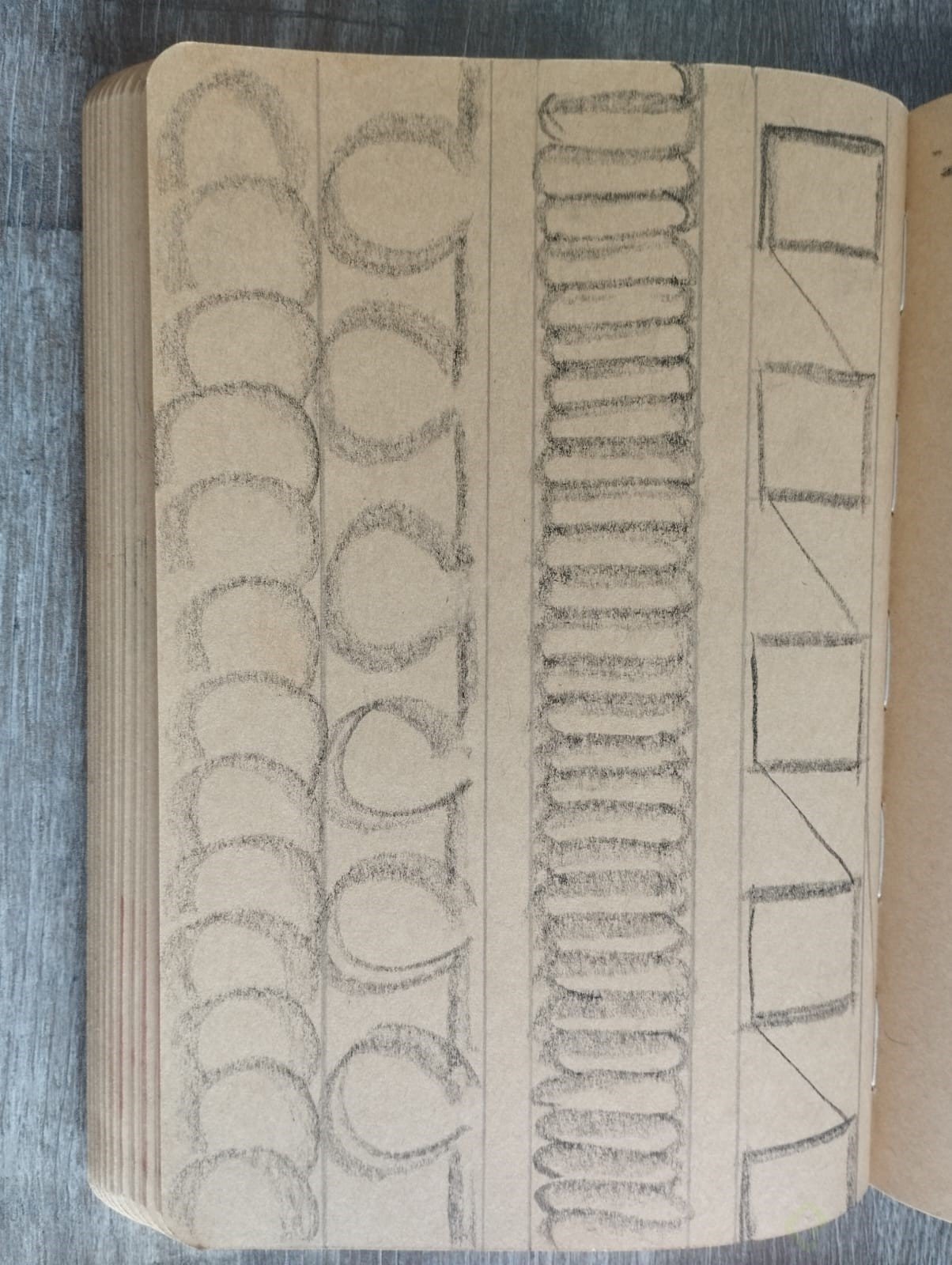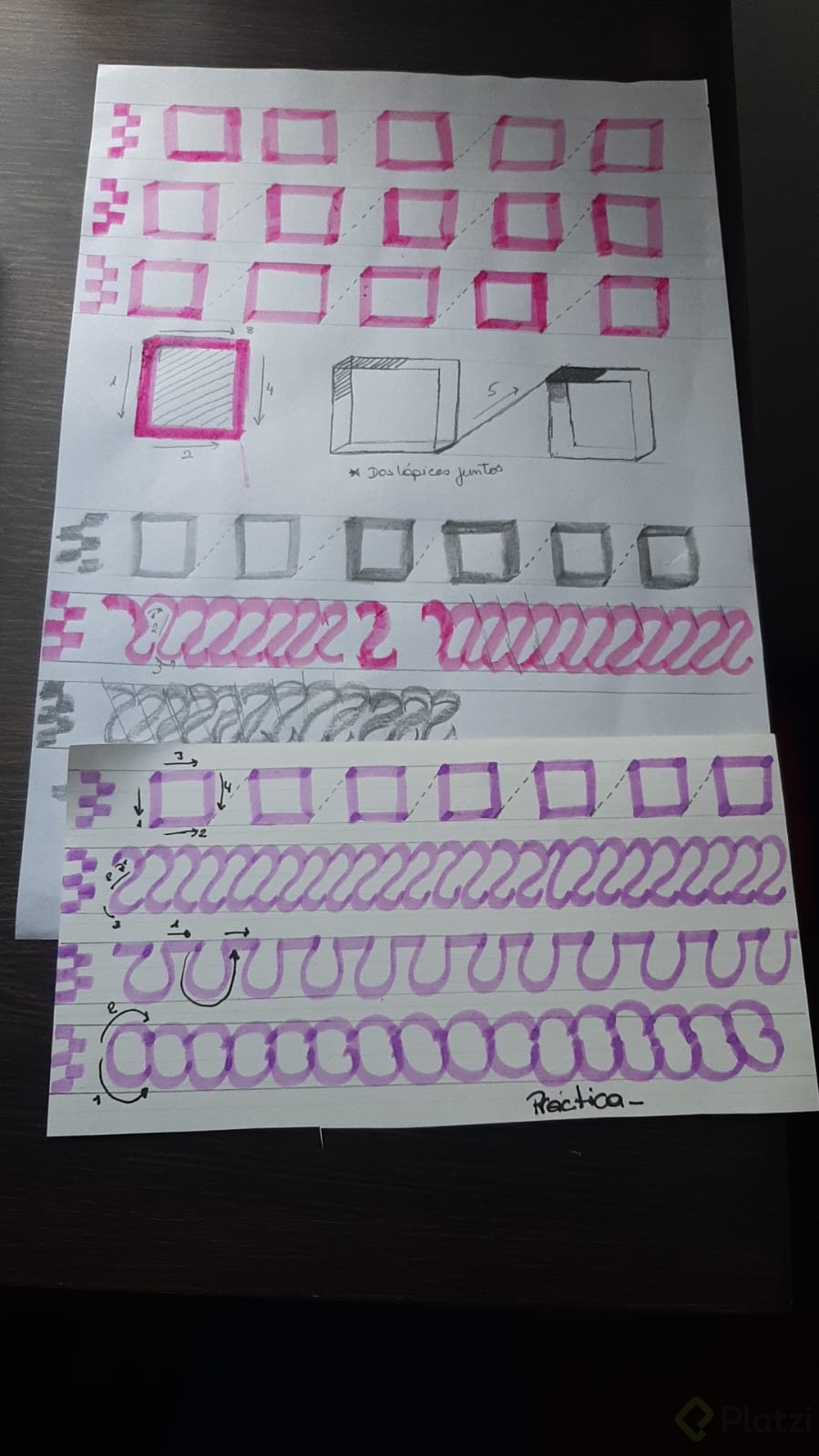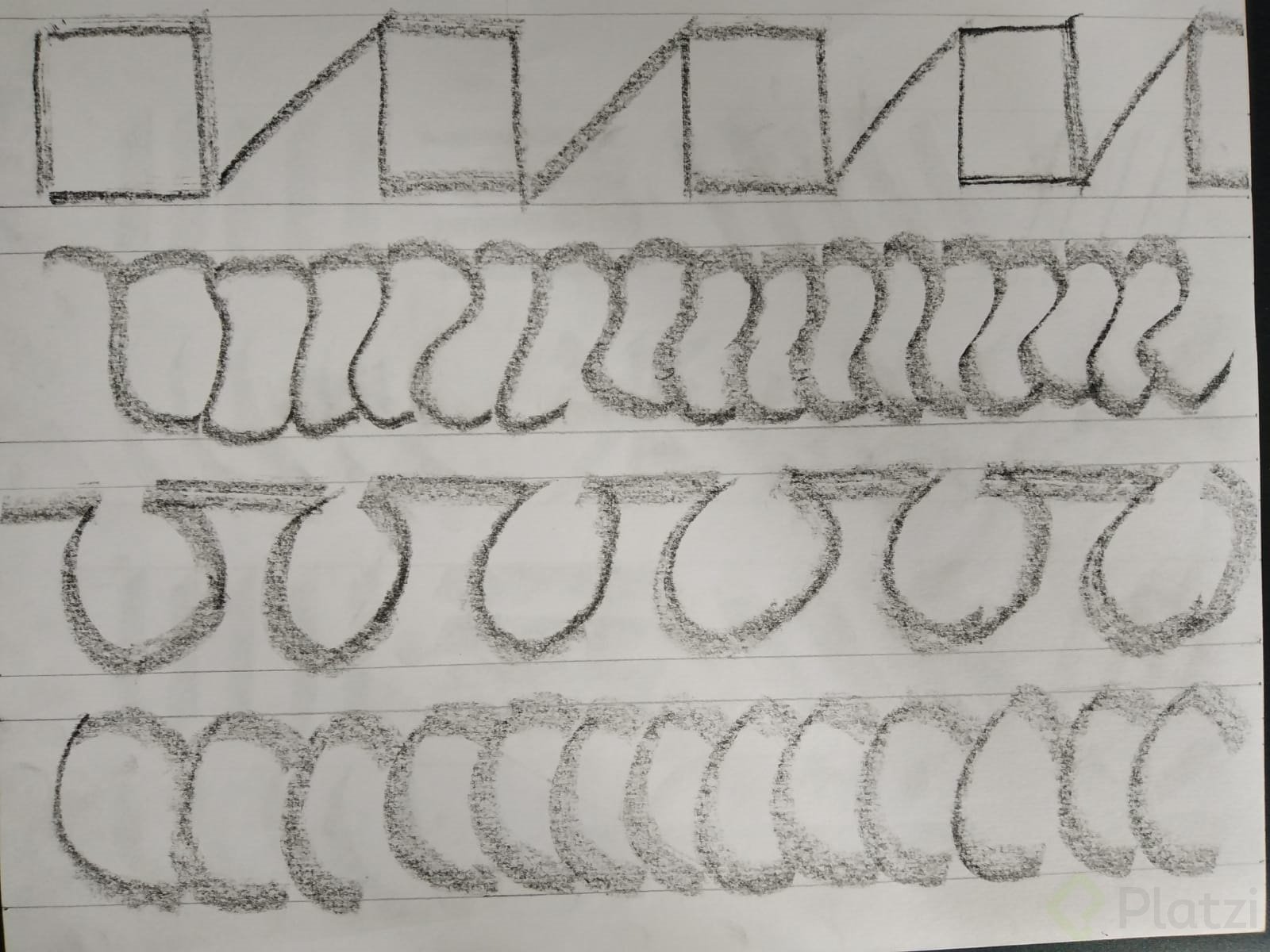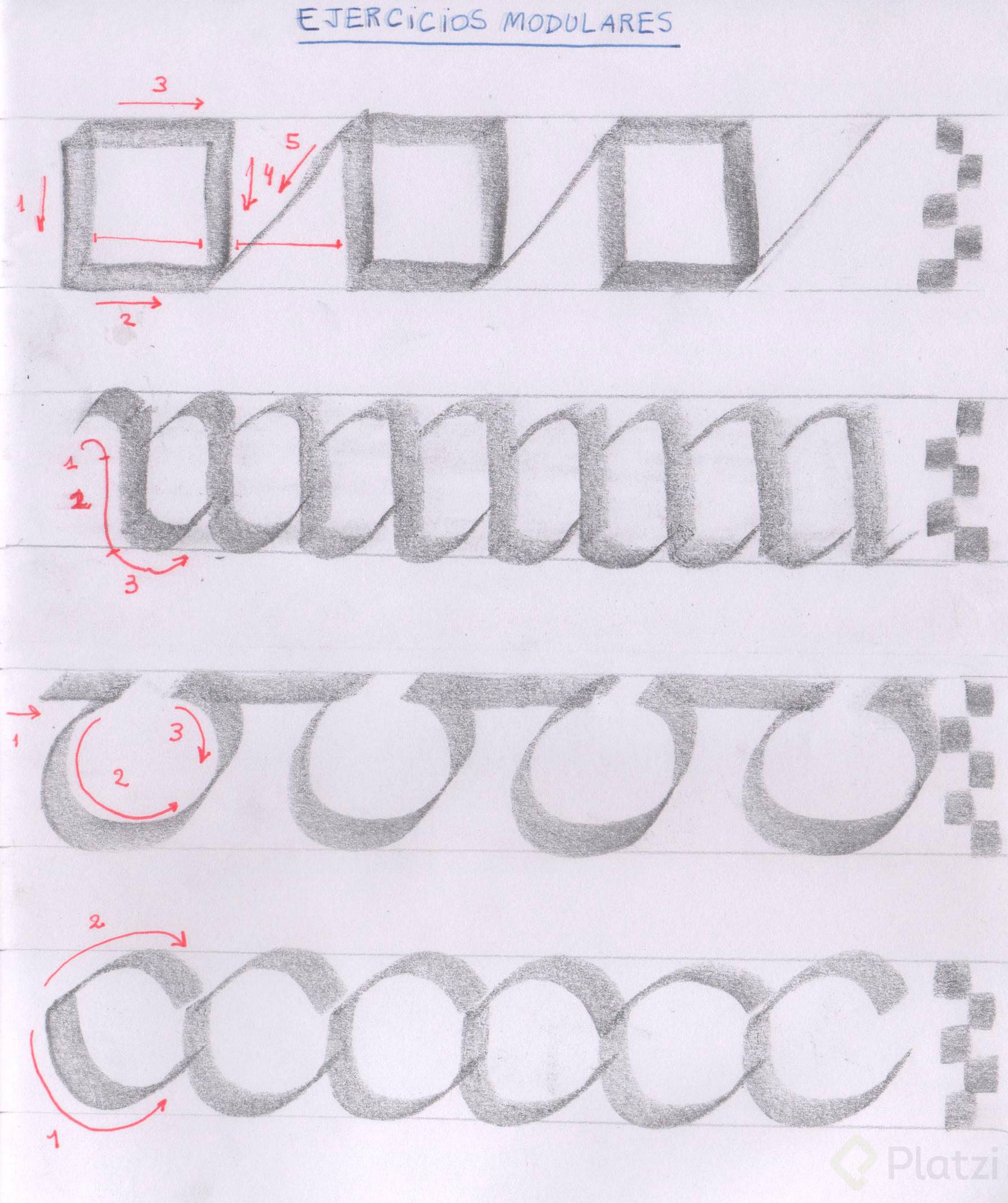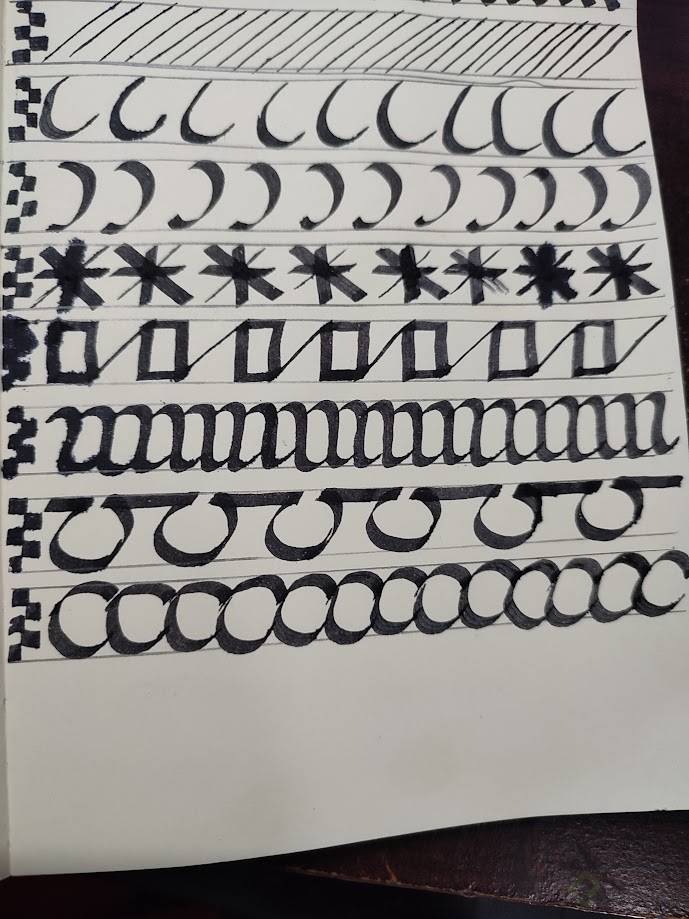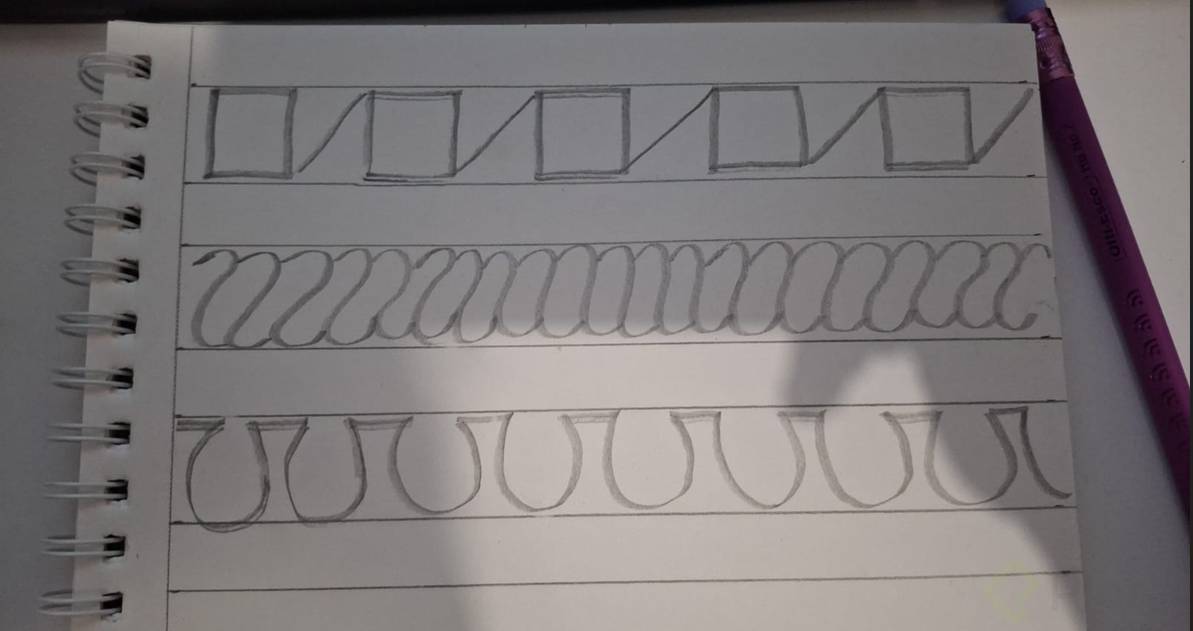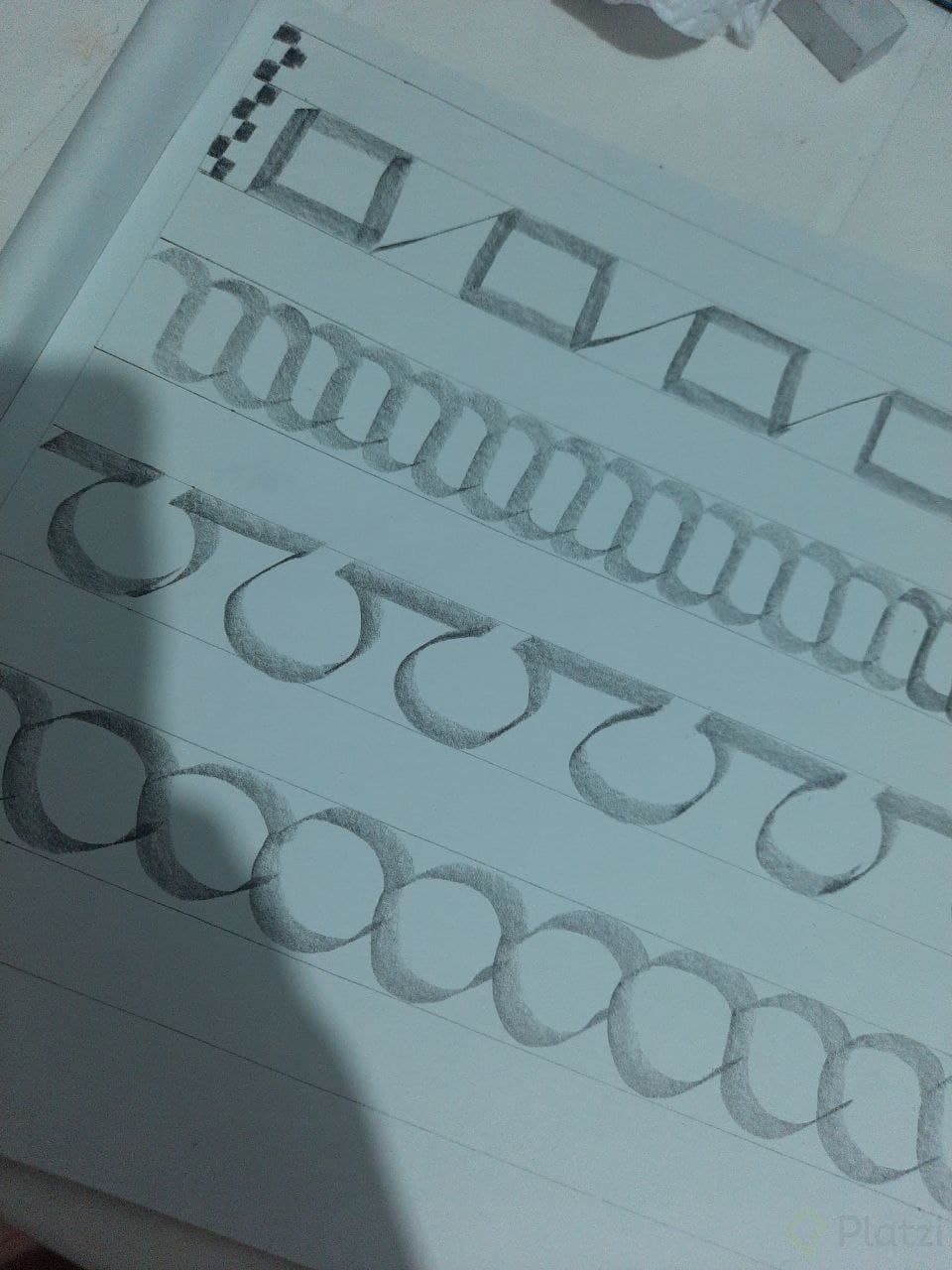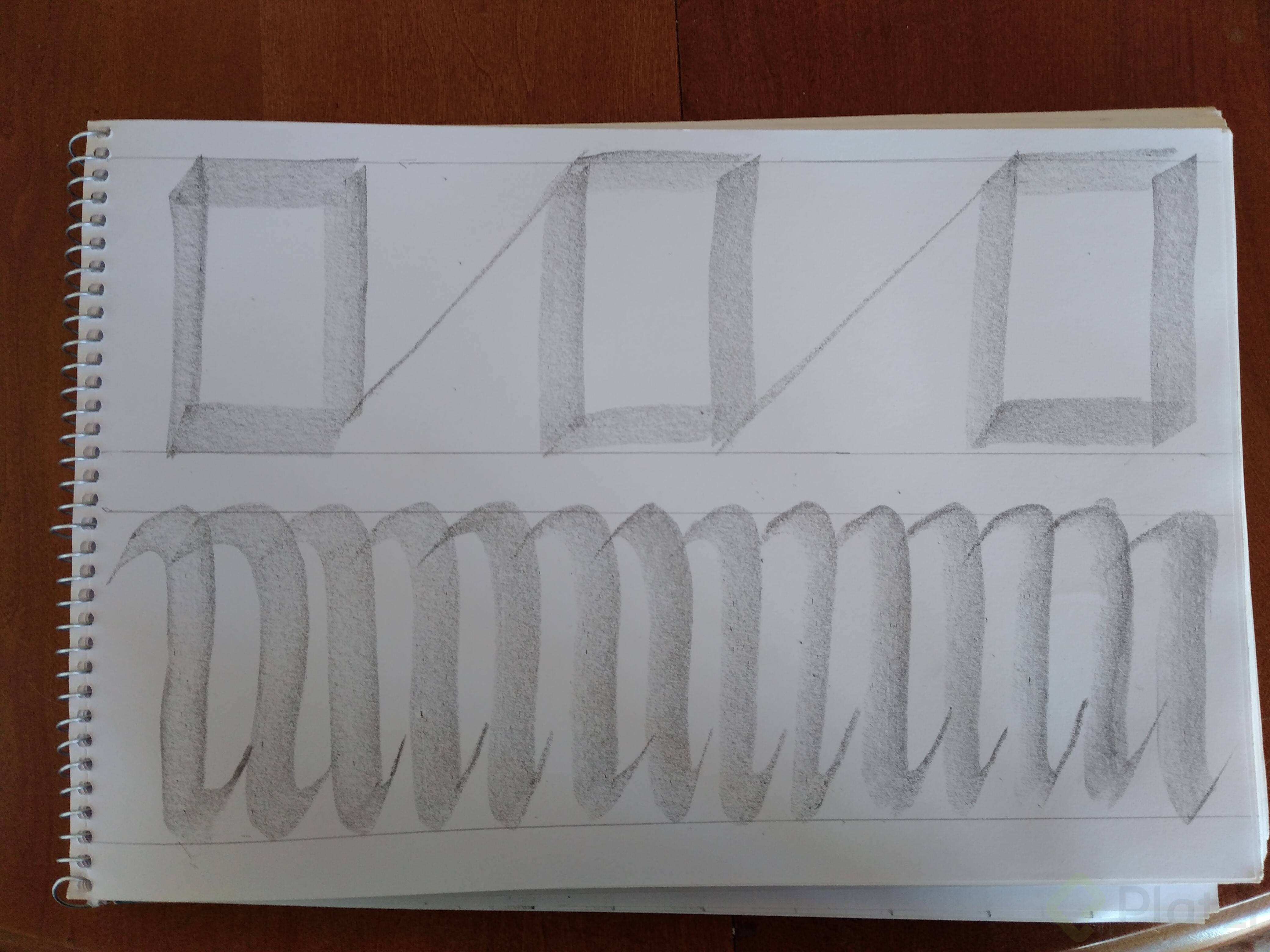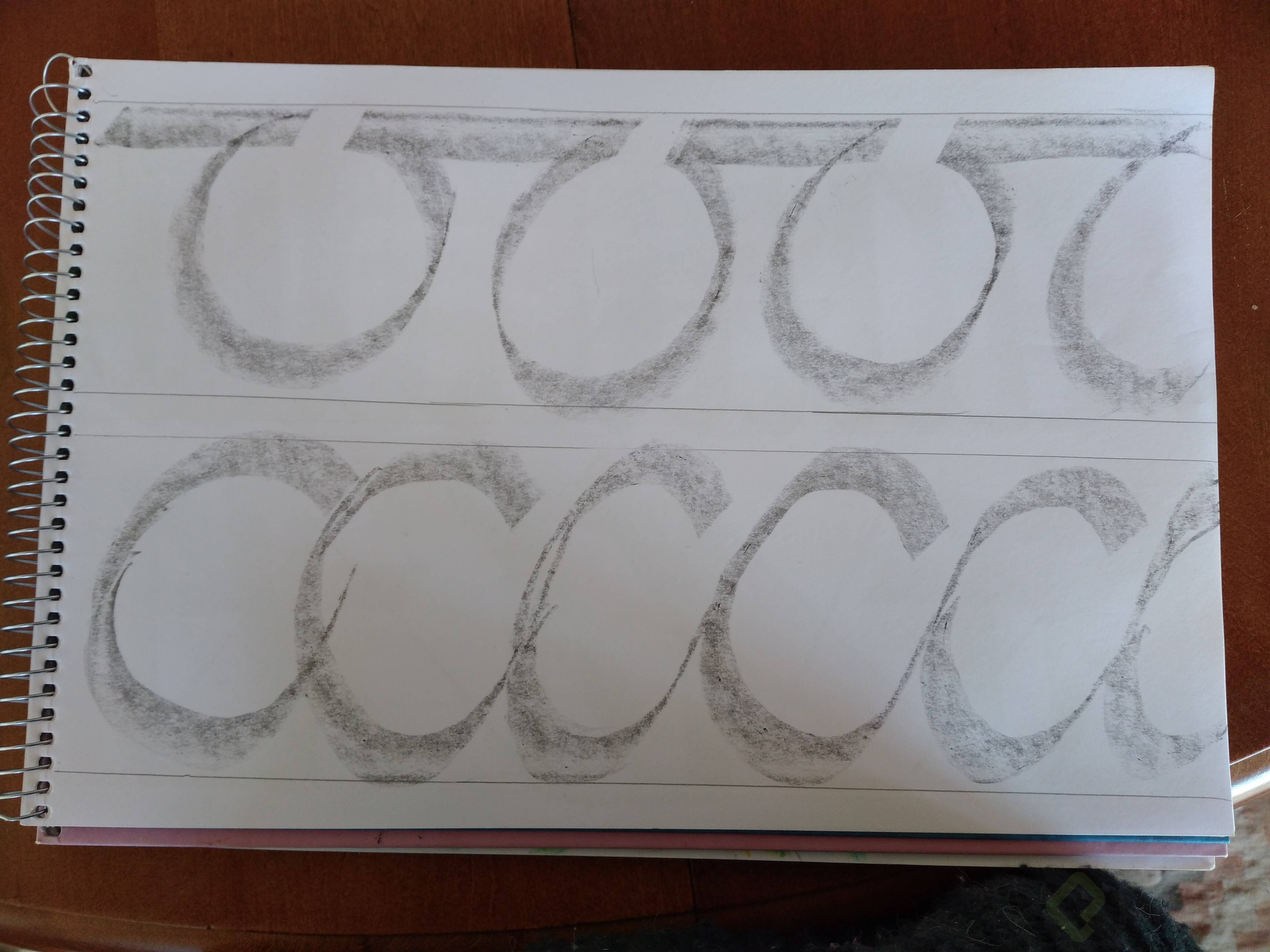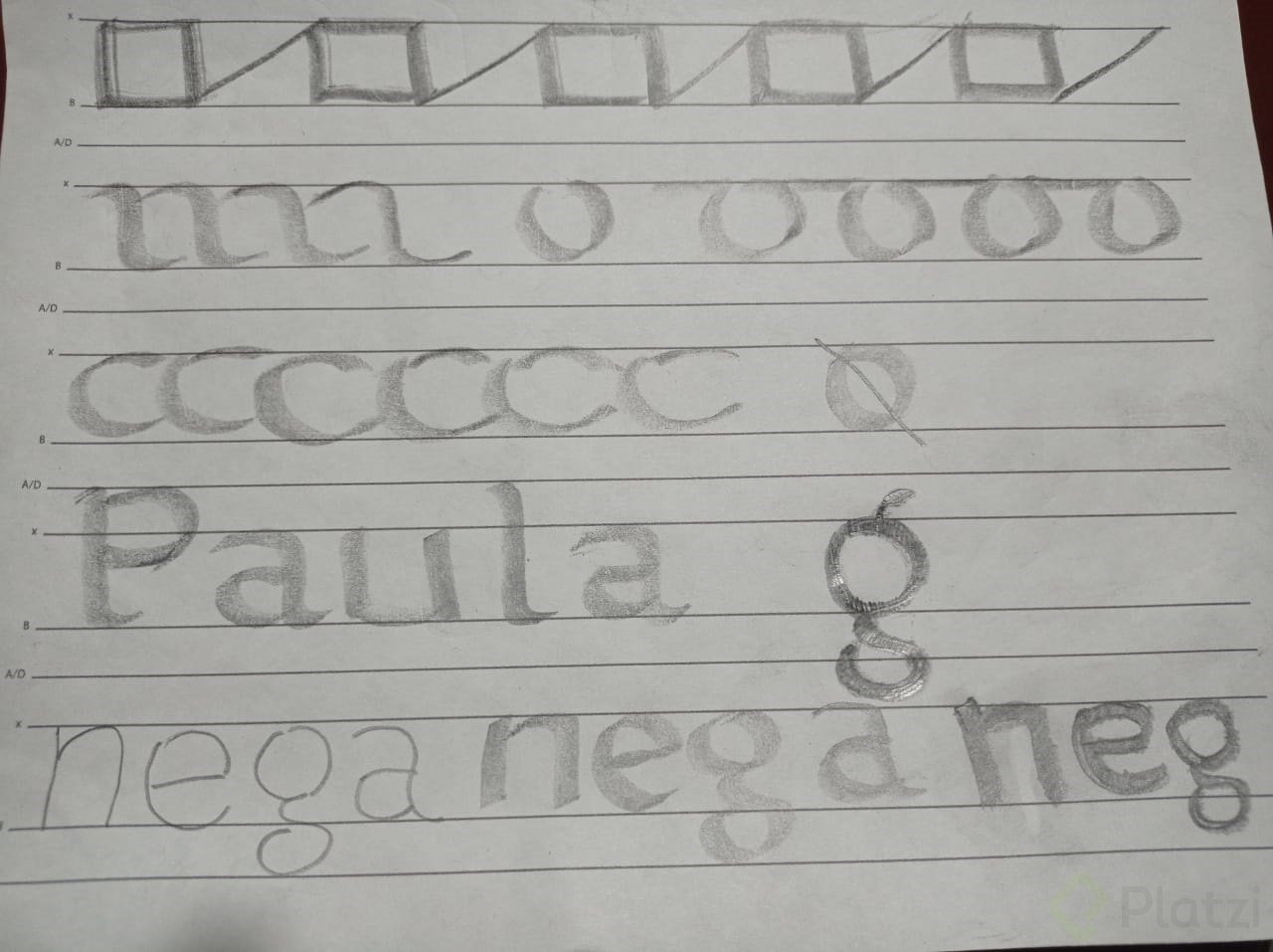
Ejercicios modulares básicos
La caligrafía es mucho más que simples trazos en un papel.
Es un arte que requiere precisión, creatividad y una comprensión profunda de la estructura tipográfica.
En esta lección, exploraremos ejercicios clave inspirados en un enfoque pedagógico innovador para niños, diseñado por el calígrafo Tom Gourdie.
No solo enseñan a escribir, sino también a entender la forma y el ritmo de las letras de una manera lúdica y efectiva.
¿Cómo se hace el ejercicio del cuadrado?
El ejercicio del cuadrado es fundamental para entender los ángulos y la coordinación mano-ojo en caligrafía.
Sigue estos pasos:
- Paso 1: traza una línea de arriba hacia abajo. Recuerda mantener el ángulo de la pluma en 45 grados.
- Paso 2: traza de izquierda a derecha.
- Paso 3: otra línea de izquierda a derecha, pero superior.
- Paso 4: finalmente, una línea desde la parte derecha, de abajo hacia arriba.
El quinto trazo es especial, ya que puedes hacerlo de derecha a izquierda o viceversa, dependiendo de cómo te resulte más cómodo.
El espacio entre los cuadros debe ser similar al espacio interno de cada uno.
Esto genera un ritmo visual uniforme.
Las uniones deben parecer un "click", creando empalmes casi tridimensionales que enriquecen la estética de las formas.
¿Qué es la repetición de 'n' y cómo se realiza?
Las 'n' repetitivas son un excelente ejercicio para mantener la simetría y el ritmo caligráfico.
Se realizan en tres pasos:
- traza el primer trazo redondeado, similar a un hombro.
- haz una pausa al descender.
- continúa con el siguiente trazo.
Este ejercicio enfoca la atención en la uniformidad de los espacios.
Además, es crucial que el recorrido de la pluma caligráfica sea homogéneo en ambas direcciones para crear una apariencia fluida.
¿Cómo se generan las llaves o candados repetitivos?
Este ejercicio parece sencillo, pero tiene complejidades que ayudan a mejorar la precisión caligráfica.
Sigue estos pasos:
- Paso 1: traza el primer arco asegurándote de mantener un espaciado coherente entre las uniones.
- Paso 2: continúa con el siguiente arco, respetando el diseño anterior.
- Paso 3: vuelve al punto inicial para completar la figura.
Estos movimientos repetitivos son claves para dominar letras como 'o' o 'y'.
El enfoque aquí es en la uniformidad del espacio, la cual genera una comprensión más profunda de las interacciones de las formas tipográficas.
¿Qué otros ejercicios pueden mejorar tu habilidad caligráfica?
Más allá de los ejercicios específicos mencionados, la práctica constante y el análisis de las formas ayudan a desarrollar habilidades fundamentales en la tipografía.
¿Por qué son importantes los ejercicios escalonados?
Los ejercicios escalonados, como las repeticiones de escalas, crean texturas interesantes y trabajan el ángulo de la pluma.
Este proceso mental ayuda a observar más allá de la simple forma.
La clave está en entender los trazos como bloques modulares que generan ritmo y textura.
¿Cómo influye la presión, el espacio y el color en la caligrafía?
Cada trazo debe ser una reflexión cuidadosa sobre estos elementos:
- Presión: controla el grosor del trazo.
- Espacio: asegura que las letras tengan un flujo rítmico.
- Color: aporta una dimensión estética que complementa la estructura.
El objetivo es no solo trazar, sino también pensar en cómo afectan estos factores a la composición global de la escritura.
¡Continúa practicando estos ejercicios y observa cómo tu habilidad caligráfica mejora cada día!
Explorar la caligrafía te abrirá las puertas a un mundo lleno de arte y expresión personal, mientras enriqueces tus habilidades en el manejo de la escritura manual.